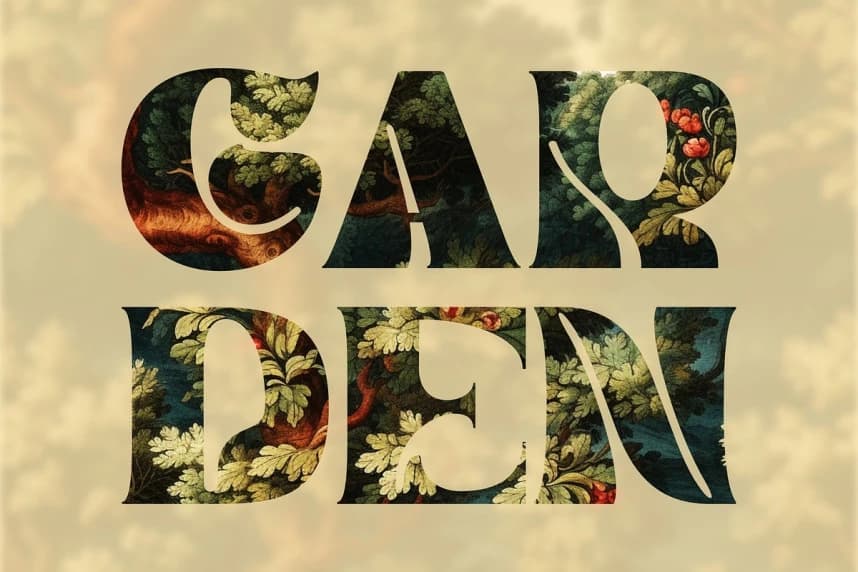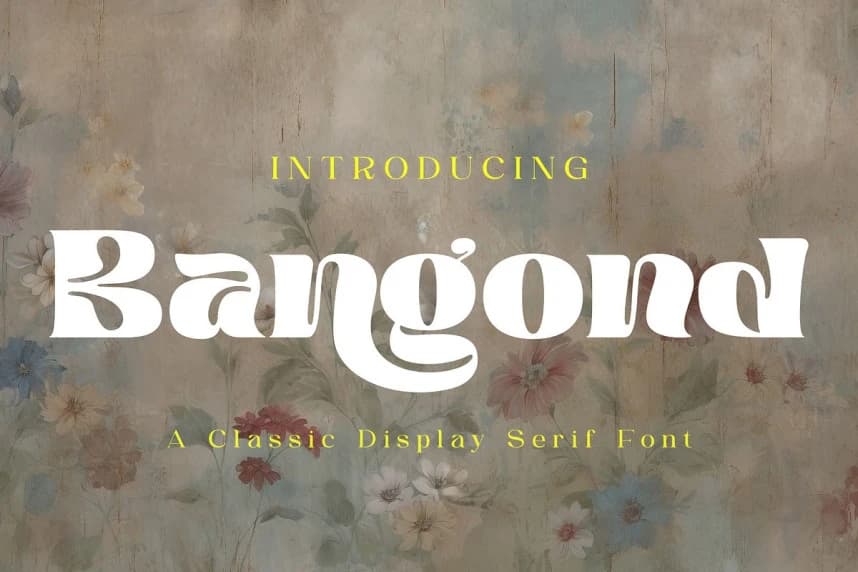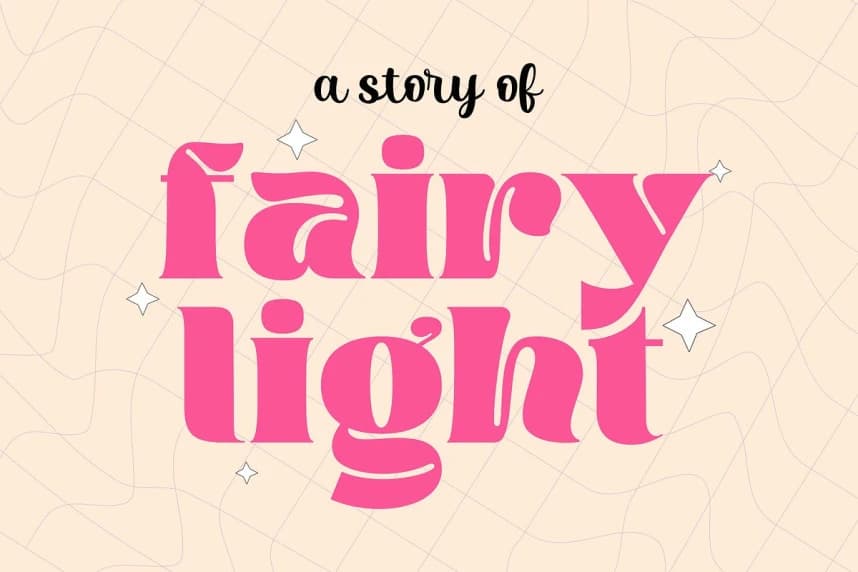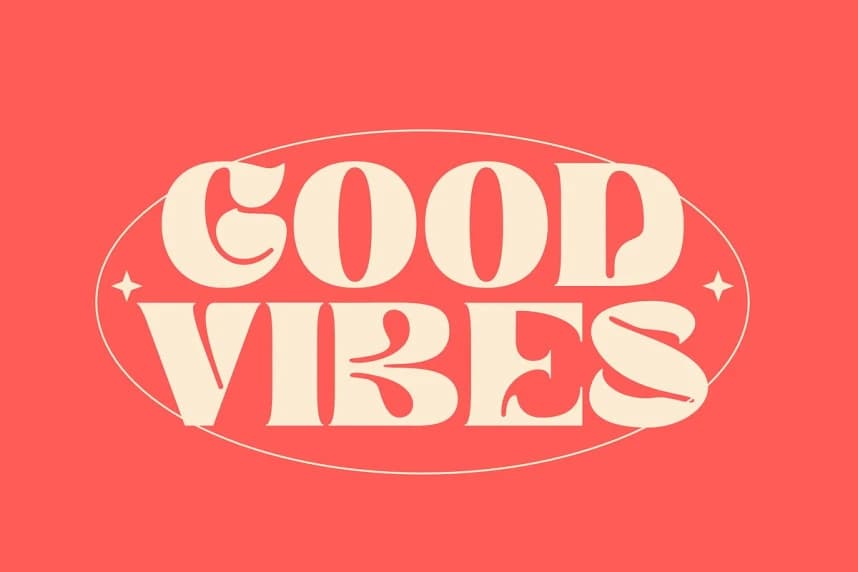
Bangond Font, zarafeti etkileyici bir güçle kusursuzca birleştiren zamansız bir serif fontudur. Biraz bracketli seriflere ve yatay vurguya sahip olan Bangond, sofistike bir hava yayıyor. Açık counter'lar ve kalın ile ince çizgiler arasındaki ılımlı kontrast, okunabilirliği sağlar.
Bangond Font, zarafeti etkileyici bir biçimde sorunsuzca birleştiren zamansız bir serif yazı tipidir. Bangond Font hafifçe kemerli seriflere ve yatay vurguya sahip olan sofistike bir etki yaratır. Açık iç boşluklar ve kalın ile ince çizgiler arasındaki ılımlı kontrast okunabilirliği sağlar.